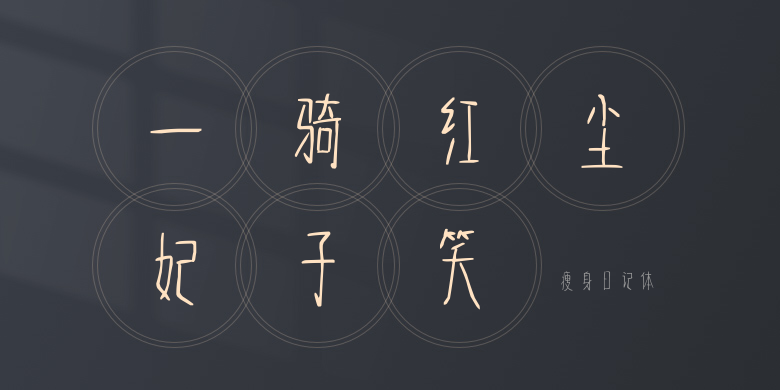
瘦身日记体
瘦身日记体,这款字体结构工整、笔画清晰,兼顾美观与易读性,适用于标题、正文、海报、包装、LOGO 等多种场景。字形优雅稳定,风格百搭耐看,适配日常排版与创意设计,让文字呈现更舒适、更具质感。瘦身日记体一笔一画,皆是细节,以均衡的比例、流畅的线条打造舒适视觉体验,字形端正大气,风格简约现代。无论是商业设计、品牌宣传还是日常排版,都能轻松驾驭,让文字更有格调与力量。瘦身日记体字体下载。